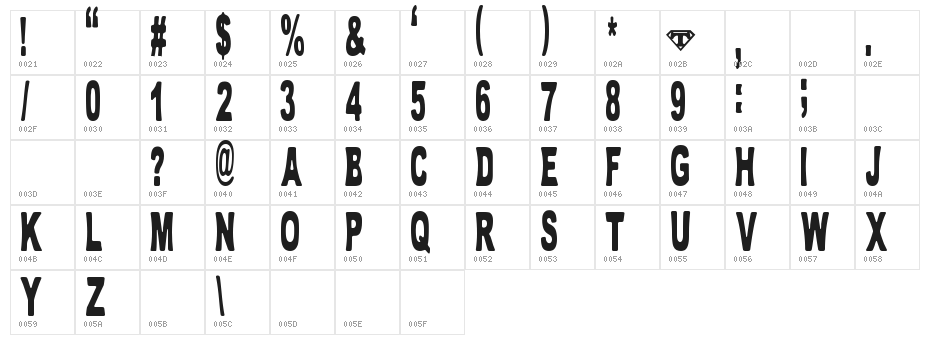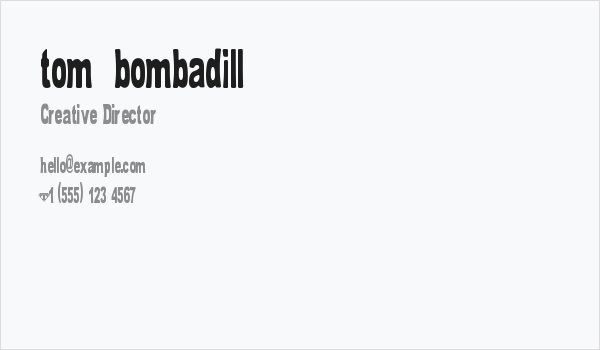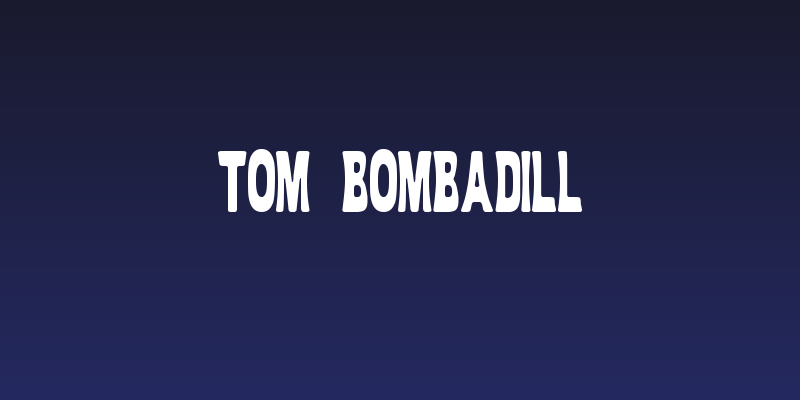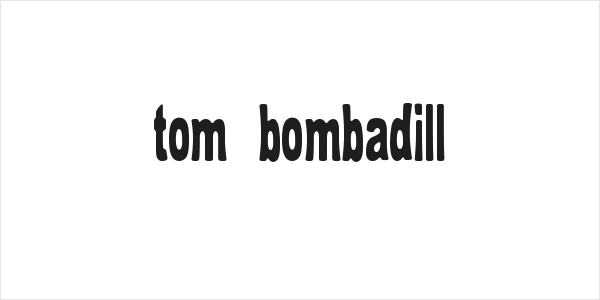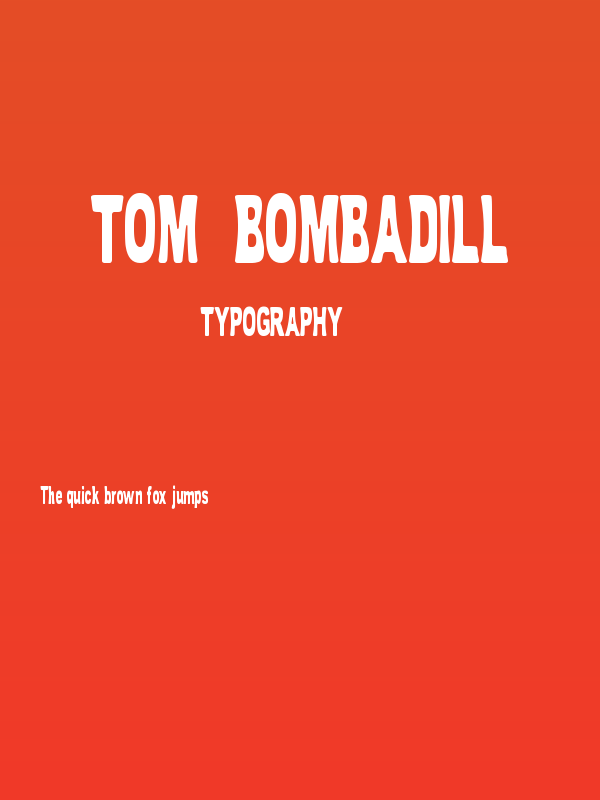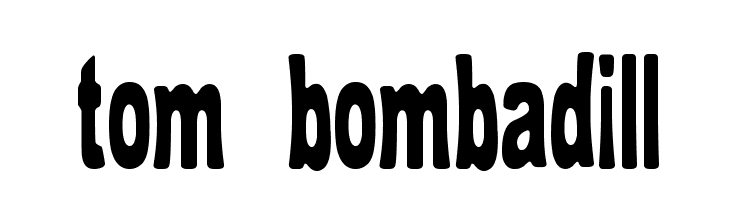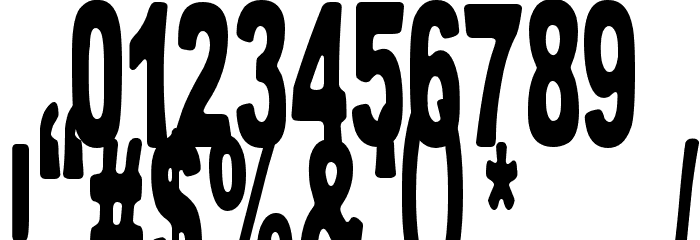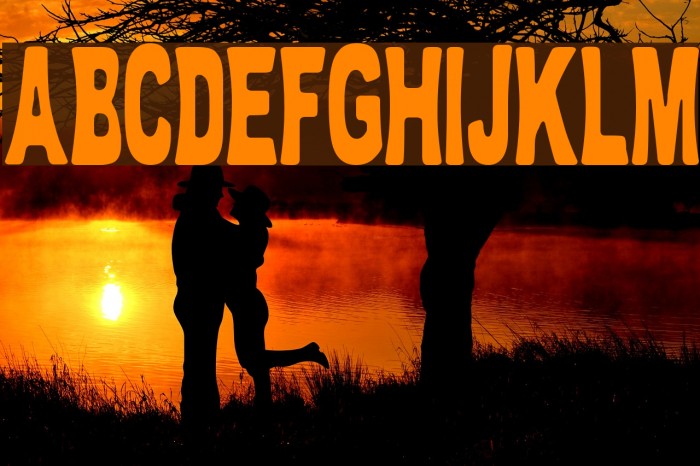
tom_bombadill Font
✎ Crazy
| Style général | Vintage, Playful |
| Projets proposés | Ideal for children's books, playful branding, comic strips, and creative posters. |